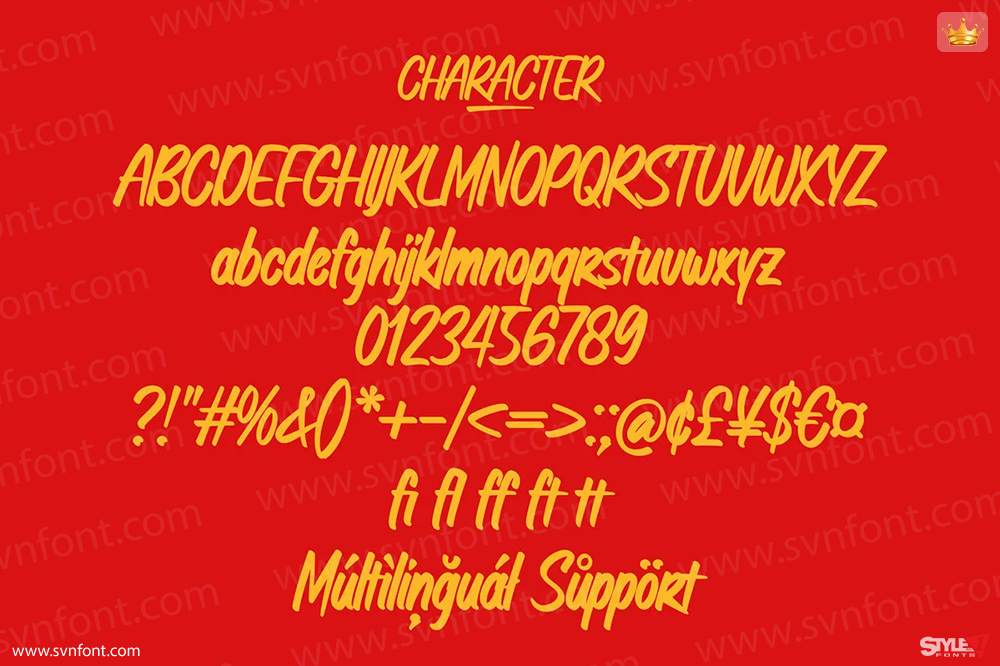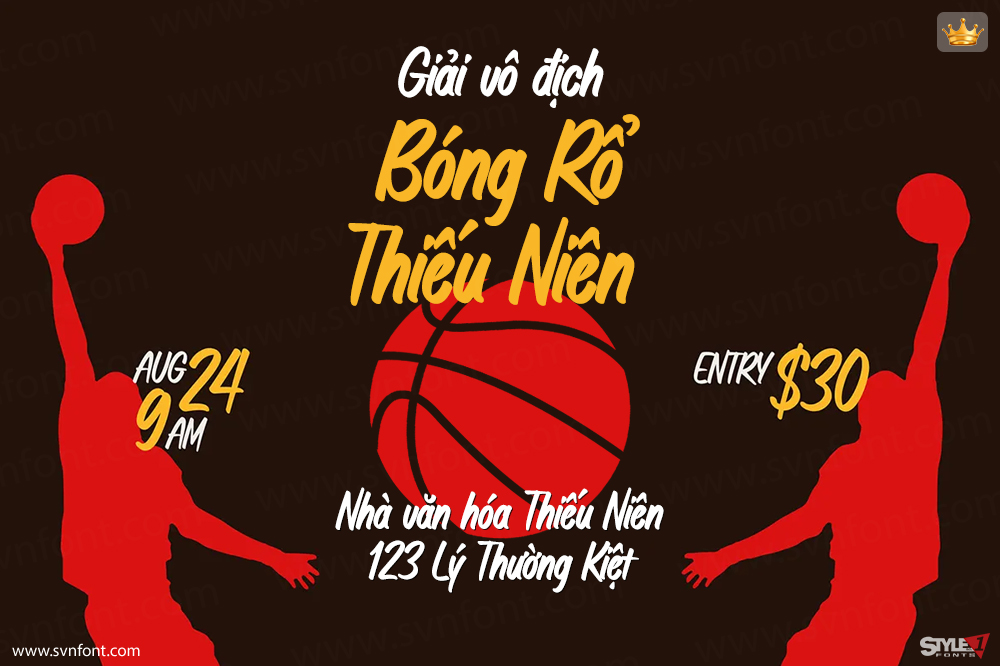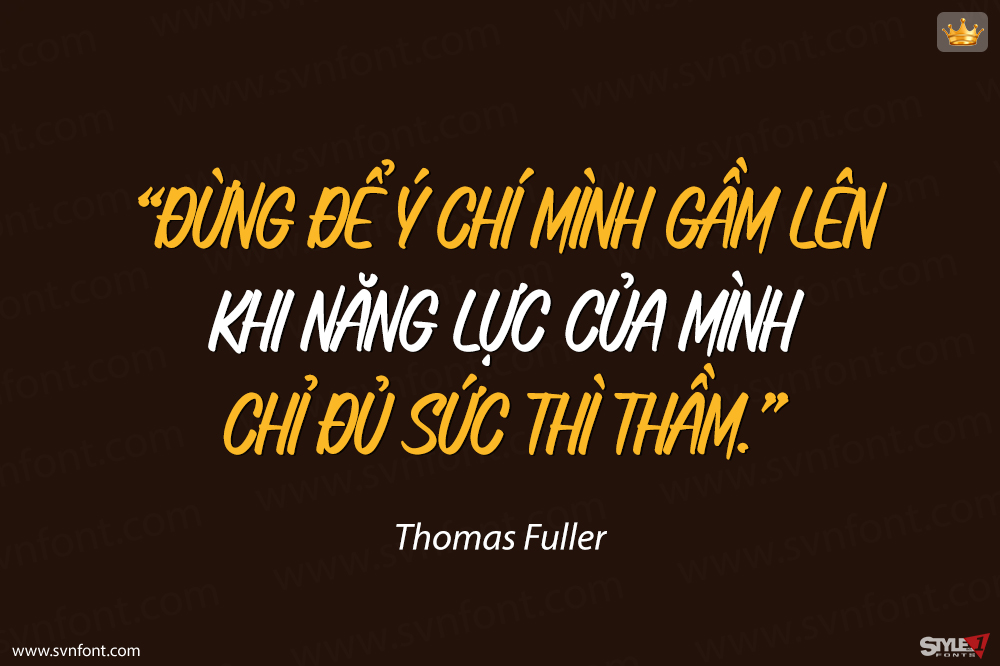
Mooncrack là một phông chữ theo phong cách viết tay với những nét chữ đậm và mạnh mẽ. Kiểu chữ này thu hút sự chú ý với các hình dáng chữ cái dày và đậm, khiến nó trở thành một lựa chọn lý tưởng cho các dự án thiết kế đòi hỏi sự hiện diện thị giác mạnh mẽ. Nó phù hợp cho nhiều dự án thiết kế khác nhau như logo, xây dựng thương hiệu, áp phích, trích dẫn, thiết kế bao bì, nhãn mác và nhiều hơn nữa!
Nhà thiết kế: Dwi Ahidian
Nhà phát hành: Lemonthe